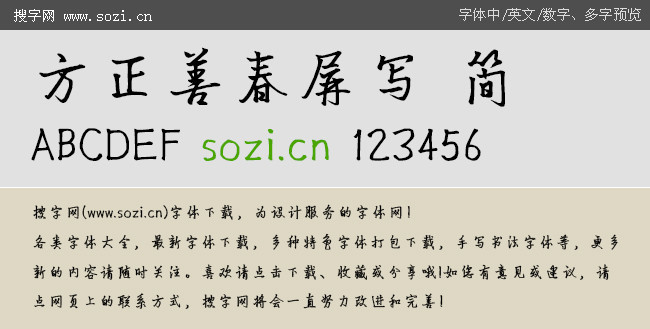
方正善春屏寫簡體
搜字網(wǎng)提供一款方正善春屏寫簡體字體下載,方正善春屏寫簡體是一款漂亮的手寫字體,該字體筆畫光結(jié)統(tǒng)計(jì),結(jié)構(gòu)流暢優(yōu)美,而且筆畫有一種蒼勁有力的感覺,整體上給人一種偶雅的氣勢,并且擁有一種現(xiàn)代美感,適合應(yīng)用于海報(bào)設(shè)計(jì)、書籍排版、包裝設(shè)計(jì)等應(yīng)用。(本字體為個(gè)人非商用版,如需要商用請(qǐng)聯(lián)系方正公司購買版權(quán))